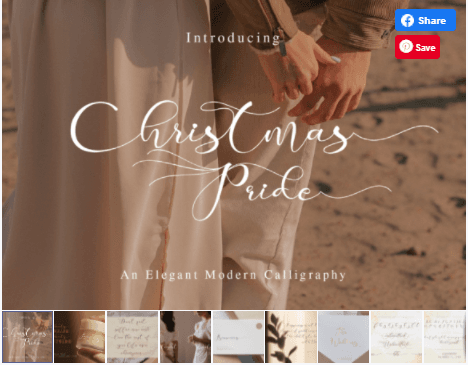
Christmas Pride Font
Christmas Pride - тонкий, элегантный и плавный рукописный шрифт. У него красивые и хорошо сбалансированные персонажи, и, как следствие, он соответствует широкому кругу дизайнов. Этот шрифт закодирован в кодировке PUA, что означает, что вы можете легко получить доступ ко всем глифам и штрихам!